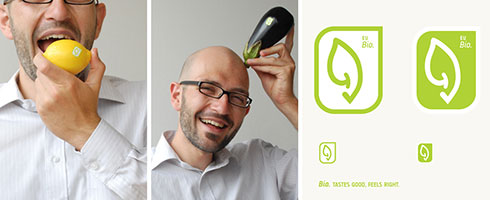
Seit dem 8. Dezember 2009 dürfen die Bürger der Europäischen Union über ein neues, einheitliches Biologo abstimmen (Fontblog berichtete: EU-Biologo: es darf abgestimmt werden). Zur Auswahl stehen 3 Entwürfe, von denen eine internationale Jury eines präferiert hatte. Inzwischen wirbt auch ein Videoclip auf YouTube für die Abstimmung, die am 31. Januar 2010 endet:
Nun meldet sich der Entwerfer vom Logo Nummer 2 zu Wort, in Kommentar 53 zum oben verlinkten Fontblog-Beitrag. Er heißt David D. Holly, wurde 1980 in Mainz geboren und studierte dort Kommunikationsdesign. Auf einer eigens eingerichteten Webseite schreibt er über seinen Entwurf: »Die Intention meines Beitrages ist die Entwicklung einer freundlich-spielerischen Wort-Bildmarke, die im Kontext organischer EU-Produkte steht und infolge effizienter Öffentlichkeitsarbeit zum positiven Effekt und Mehrwert von Natürlichkeit und Menschlichkeit aufklären soll.« Im Rahmen anderer Projekte konnte Holly bereits Erfahrungen auf Ebene der Europäischen Union gewinnen.
Das Basiselement seines Entwurfs ist ein stilisiertes Blatt, das in einen Haken
mündet. Obwohl in der Linienführung vordergründig ein Lächeln (Smiley) versteckt ist, lasse die Gesamtheit des Symbols, so der Entwerfer, mehrere bildhafte Interpretationen zu, wie »freches Früchtchen«, »Du bist, was Du isst!«, aber auch einen Kern, Körperteile wie ein Ohr oder der Teil eines Schwanzes.
Der Stellenwert der Zertifizierung wird durch einen typografischen Zusatz gewährleistet: »EU Bio«. Unterstützt wird das Symbol durch eine markante Hintergrundform, ein hochformatiges Rechteck. Drei Ecken sind abgerundet, die obere rechte Ecke fordere »zur Interaktion ›Probier mich!‹ auf und lässt das Logo in seiner Ganzheitlichkeit entstehen.«
Ja aber mal ehrlich “Drei Ecken sind abgerundet, die obere rechte Ecke fordere »zur Interaktion ›Probier mich!‹ auf und lässt das Logo in seiner Ganzheitlichkeit entstehen.«”
das ist doch auch meist nur dummgeschwätzt. und man dreht und erklärt es sich so wie es sich gerade verkauft.
@sir: du hast ein wesentliches wort vergessen. Herr Holly schreibt: “Drei Ecken sind HARMONISCH abgerundet, die obere rechte Ecke…”. Das ist wichtig ^^
Auch für meinen Geschmack viel zu viel Schaum. Wie da versucht wird, das Glas voll zu kriegen – absurt. so ein Verkaufs-blabla macht mich regelrecht aggressiv. Vor allem dann, wenn es so offensichtlich gemacht wird. Gibt es Menschen, die das mögen? Schlimmer als vom Versicherungsvertreter.
Übrigens halte ich es auch überhaupt nicht sinnvoll, hunderte von Interpretationen in ein Zeichen zu packen. Dann kommt nämlich so ein verwaschenes etwas raus. “Politikerlogos” könnte man diese Art nennen. Viel sagen aber nichts richtig. Mir gefällt es gar nicht – sorry – aber ich gebe einen Foto-Sympathiepunkt.
Rettet die deutsche, ach so genaue sprache? Das meint ihr doch nicht ernst? “Fighted” ist absolut ok. Alle haben verstanden was gemeint ist und auch wie es gemeint ist. Dieser anti-anglezismus kehrt anscheinend immer wieder in die diskussion zurück. Als ob sprache ein hermetisches, zu bewahrendes universum wäre.
Jetzt wirkt das Logo doch gleich viel persönlicher … Ernsthaft: beim Biss in die Zitrone fällt auf, dass das Logo keinerlei Fernwirkung besitzt, was bei einem Gang durch den farbenfrohen Supermarkt einfach notwendig ist, um klar und schnell unterscheiden zu können, was bio ist und was nicht.
In invertierter Form noch akzeptabel, aber auch da wirds auf einer Kiwi-Schale schwierig, aufgrund der detailierten Form.
Ob es gut ist und auch gut tut, wird man ja am Ende der Abstimmung sehen.
fighted ja…aber fightet?
ich hab bei dem logo immer eher an ein ohr (esel oder elf?) als ein lächeln gedacht.
Ich stelle mal eine nicht unwichtige Frage, zum öffentlichen Votingverfahren via Internet: